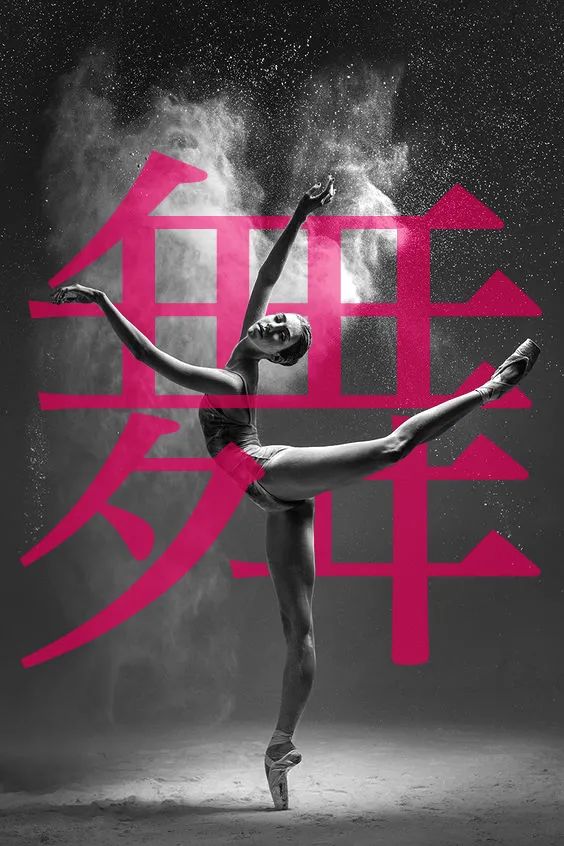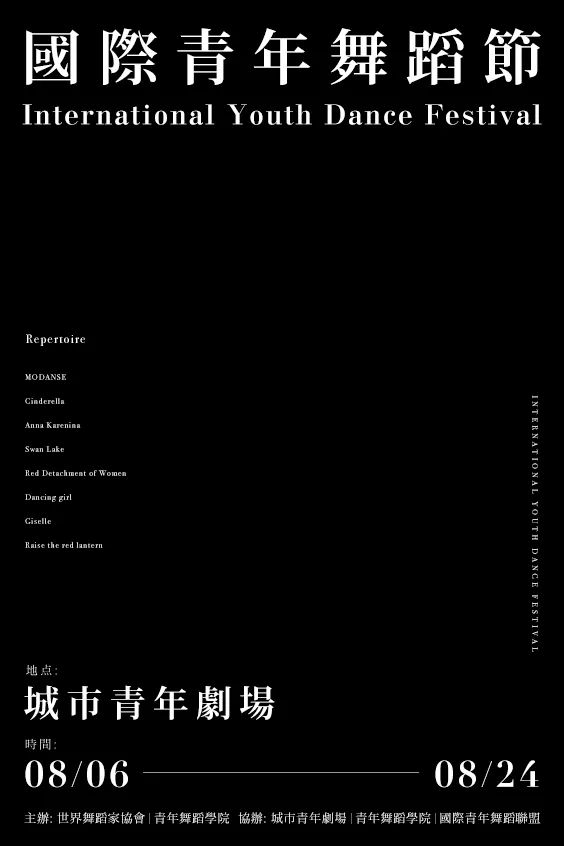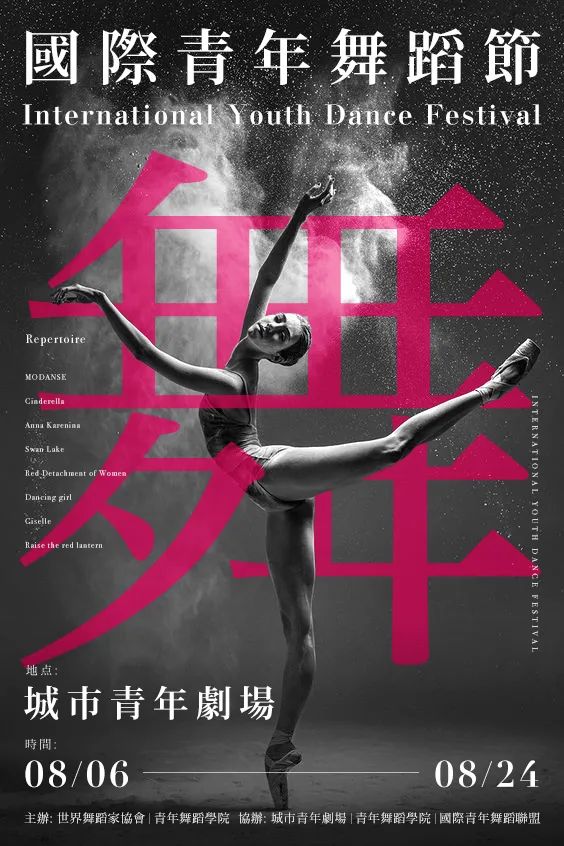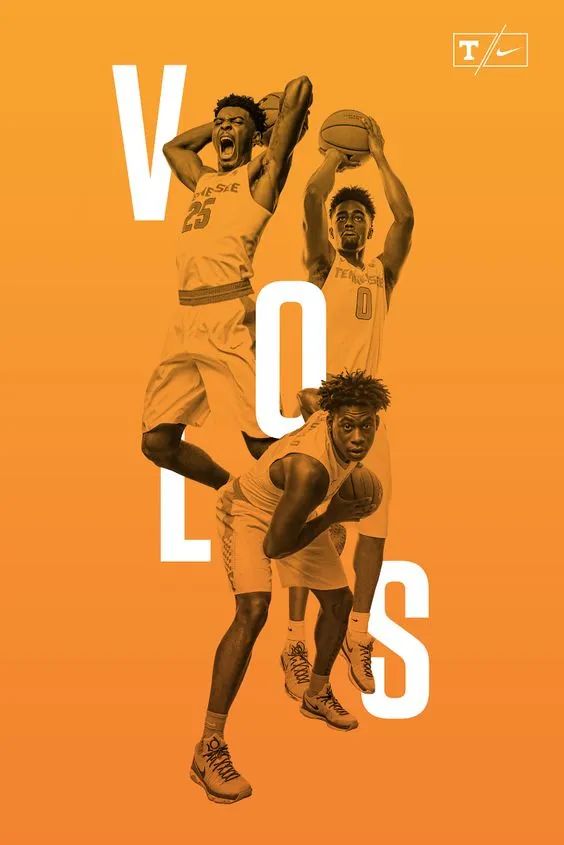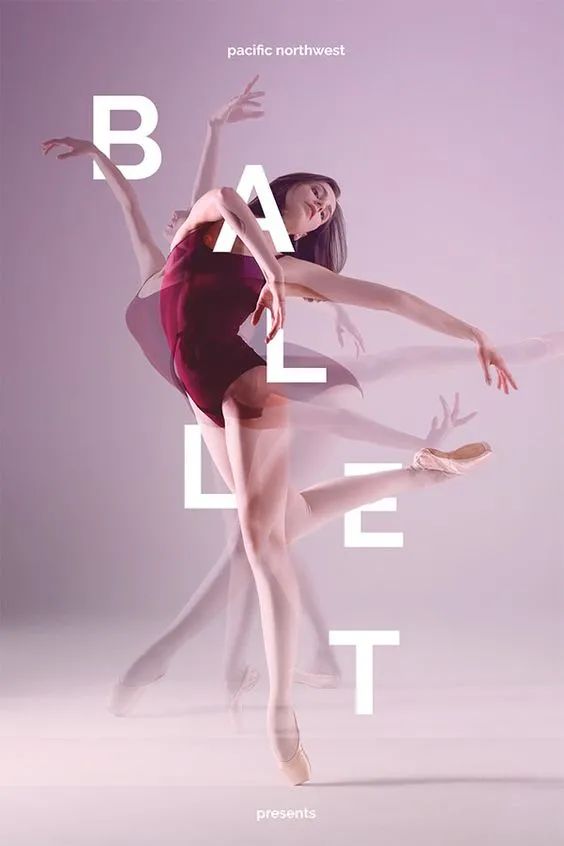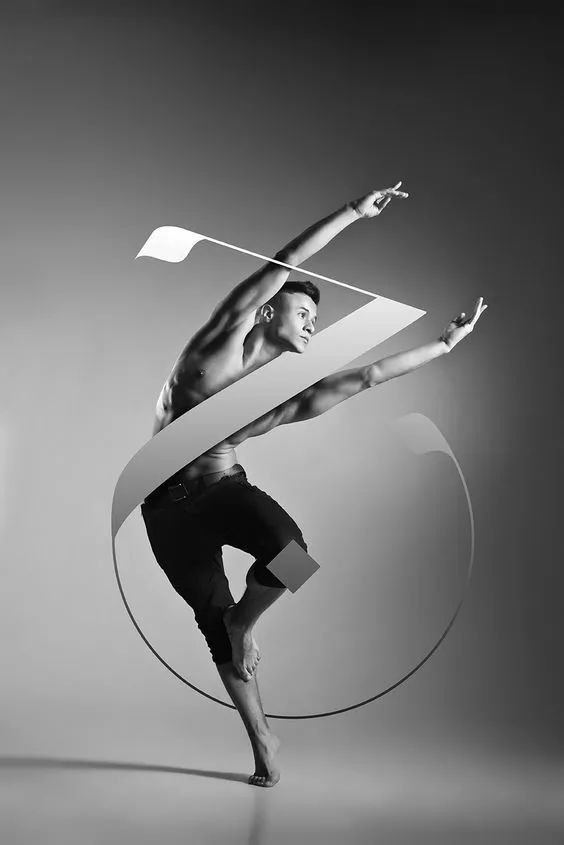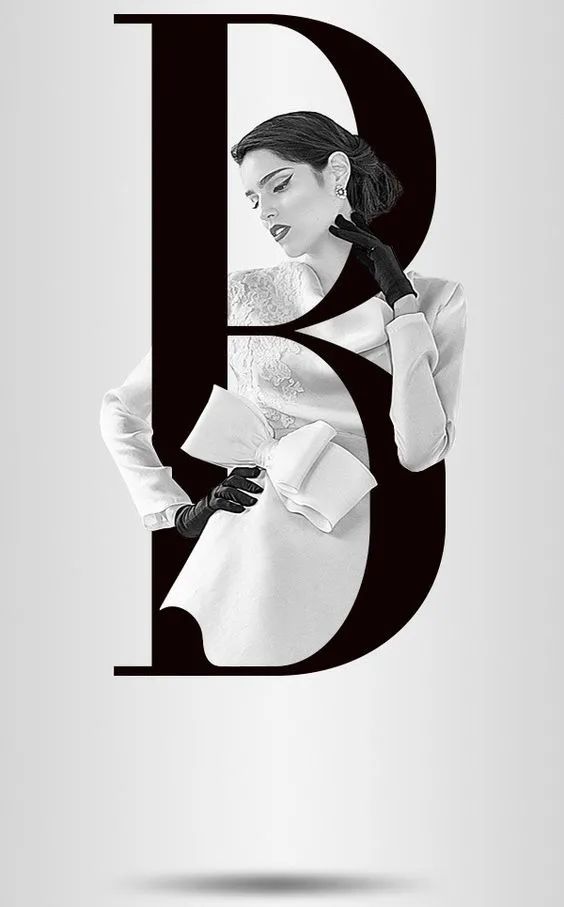
做海报缺乏灵感?巧用字体做海报:字图穿插
做海报缺乏灵感?今天这篇文章教你一种非常实用而且非常容易出效果的海报设计方法:字图穿插,这种手法在国外的海报作品中常常见到,大致可以分两类:一是字体与人的穿插,二是字体与物的穿插,我们先来看一些字图穿插的优秀设计案例:
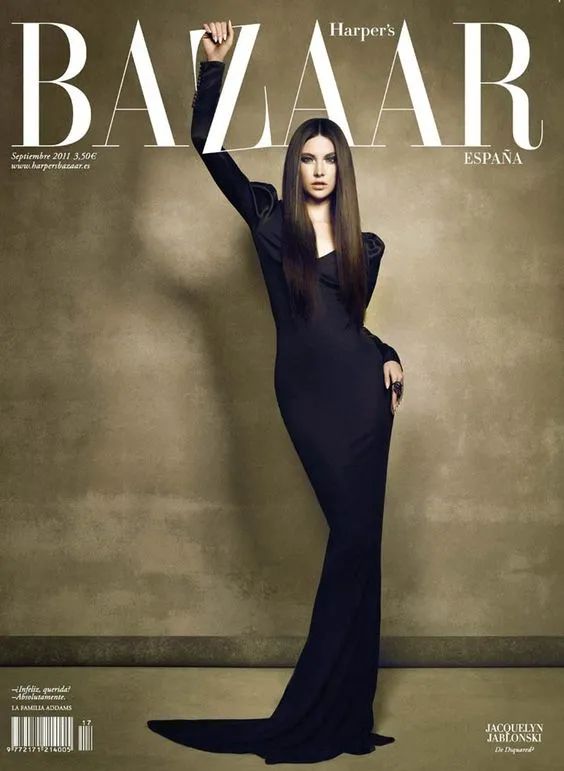
THE FIRST SORT
字体与人穿插
—
通过人物与字体在视觉上形成穿插关系,营造一种动静结合、具有空间感的独特视觉效果,非常具有视觉感染力。
THE SECOND SORT
字体与物穿插
—
除了与人物进行穿插,这种手法同样适用于与动物或静物进行穿插,就像下面的这些案例,有字体与花,字体与鱼、鸟等动物,还有字体与乐器等,通过这样一种穿插的手法营造出了丰富的空间层次关系,具有很好的视觉效果。
CASE PRACTICE
案例实操
—
接下来通过一个实操案例来学习一下如何应用字图穿插的手法来设计一张海报。
海报文案信息:
THE FIRST STEP
图片选取
—
第一步:在图片素材网站通过检索关键词 “舞蹈”、“Dance”,选取一张人物形体、舞姿及角度都不错的图片作为海报的主图。
THE SECOND STEP
字图叠加
—
第二步:选择一个合适的字体叠加在图片上方,字体的大小和位置要考虑与人物可以形成较好的穿插关系。
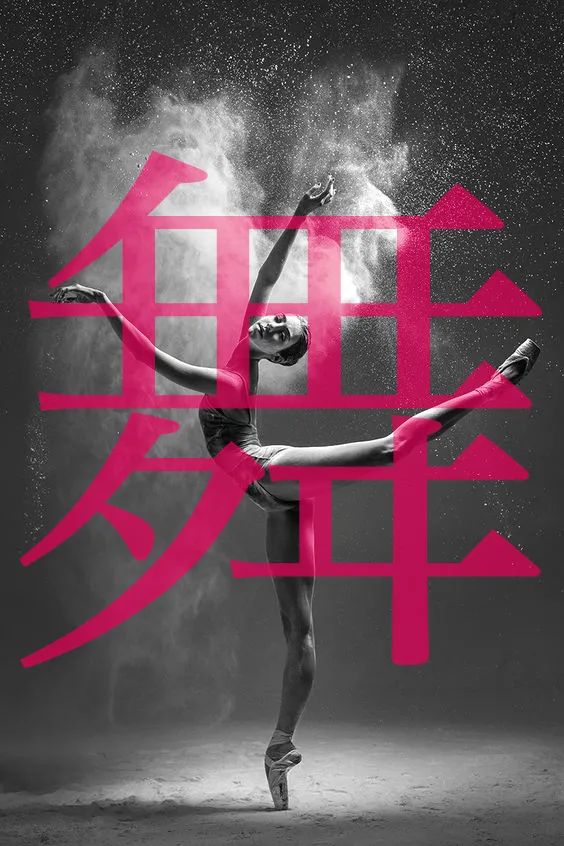
THE THIRD STEP
字图穿插
—
第三步:将字体的部分地方删去,形成与人物的穿插关系,具体方法是使用钢笔工具沿着人体结构,将要删去的字体部分选中,建立选区后删掉该部分。
THE FOURTH STEP
文字信息排版
—
第四步:对文字信息进行排版,在字体的选择上使用具有文艺气质的宋体,按照信息的主次编排文字的位置和大小,注意编排信息时考虑节奏感以及与画面主体的关系。
THE FIFTH STEP
完成海报
—
第五步:将文字信息与画面主体相结合,这种海报作品就完成了,需要注意的是,要确保文字信息在画面上清晰可见,因此部分图片区域需要做调整,如图片的底部做了暗化处理,否则主办方和协办方的信息在较亮的图片上将难以阅读。